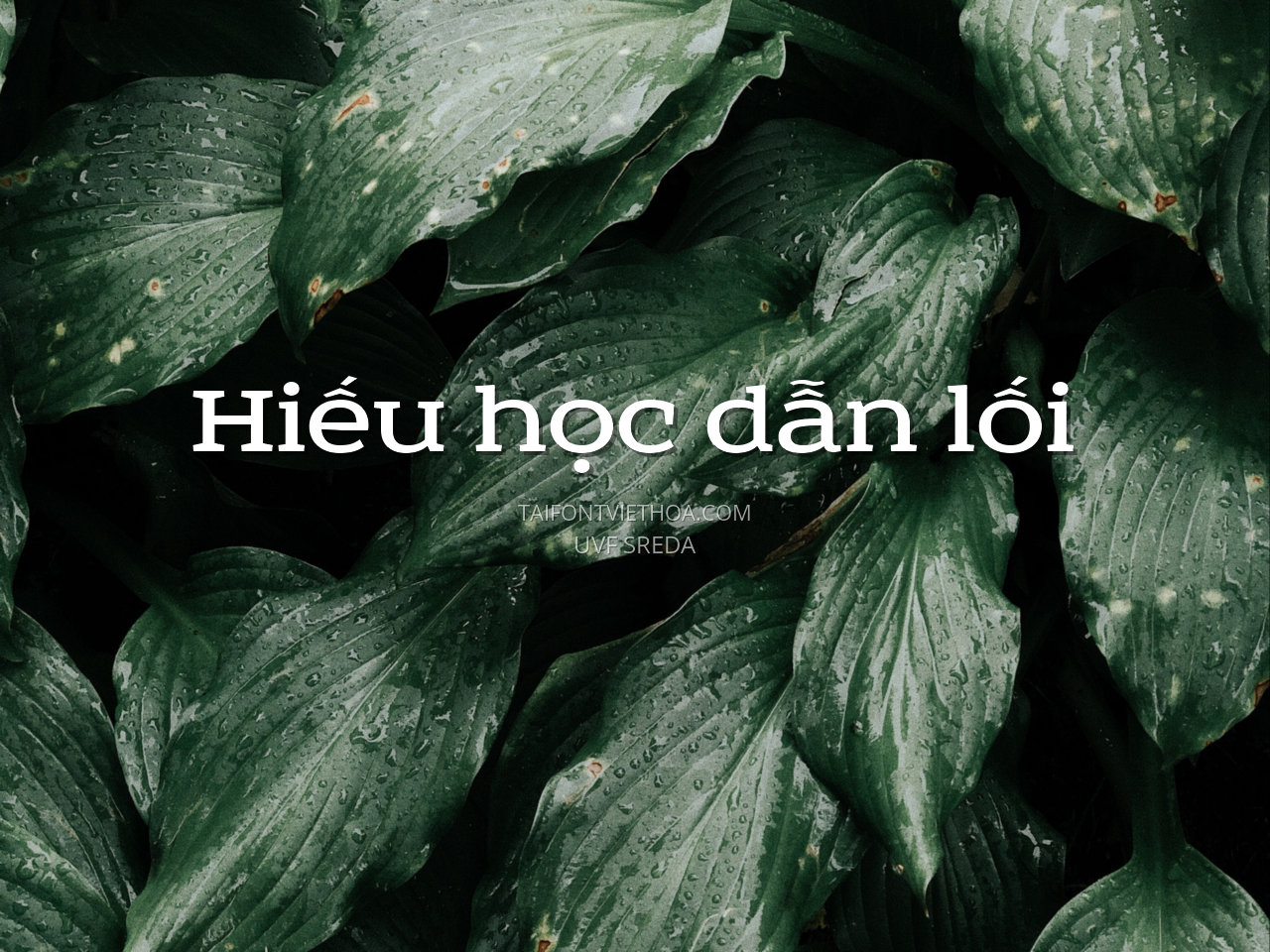
Giới thiệu về font UVF Sreda
UVF Sreda là một kiểu chữ serif hiện đại, mang hơi hướng cổ điển kết hợp cùng các yếu tố hình học cân đối. Font gốc Sreda được phát triển bởi font foundry nổi tiếng ParaType – một nhà phát hành typographic có trụ sở tại Nga, chuyên cung cấp các bộ chữ chuyên nghiệp từ những năm 1990. Font được đánh giá cao bởi khả năng cân bằng giữa tính truyền thống và ứng dụng hiện đại, hỗ trợ hơn 200 ngôn ngữ trên toàn cầu bao gồm tiếng Việt, Cyrillic, Latin và nhiều hệ ký tự châu Âu khác.
Phiên bản UVF Sreda đã được thành viên Font Chuẩn sưu tầm và chia sẻ thông qua taifontviethoa.com, sau khi đã kiểm tra khả năng hiển thị tiếng Việt đầy đủ và chuẩn hóa về mặt thẩm mỹ. Font hiện được ứng dụng rộng rãi trong thiết kế branding, tạp chí, tài liệu biên tập chuyên nghiệp và hệ thống website nội dung cao cấp.
Đặc điểm thiết kế và khả năng ứng dụng của UVF Sreda
UVF Sreda nổi bật với các đặc điểm của hệ chữ serif có chân, đường nét sắc sảo, thân chữ cao và không gian âm được phân bố tối ưu, giúp tạo cảm giác nghiêm túc và đáng tin cậy. Phần chân chữ thanh mảnh nhưng chắc chắn, kết hợp cùng các chi tiết bo tròn nhẹ ở đầu nét tạo cảm giác nhẹ nhàng, sang trọng. Font bao gồm nhiều kiểu ký tự, bao gồm chữ thường, chữ hoa, số học và các ký tự thay thế stylistic, hỗ trợ thiết kế linh hoạt trên nhiều định dạng.
UVF Sreda lý tưởng cho các thiết kế yêu cầu tính chính thống, như bản tin điện tử, biên tập tạp chí, website doanh nghiệp, hồ sơ năng lực, tài liệu quảng bá, bìa sách hay in ấn thương hiệu cao cấp. Ngành nghề phù hợp gồm: truyền thông – xuất bản, giáo dục, bất động sản, công nghệ và các dự án quảng cáo cần tính tin cậy và chuyên nghiệp.